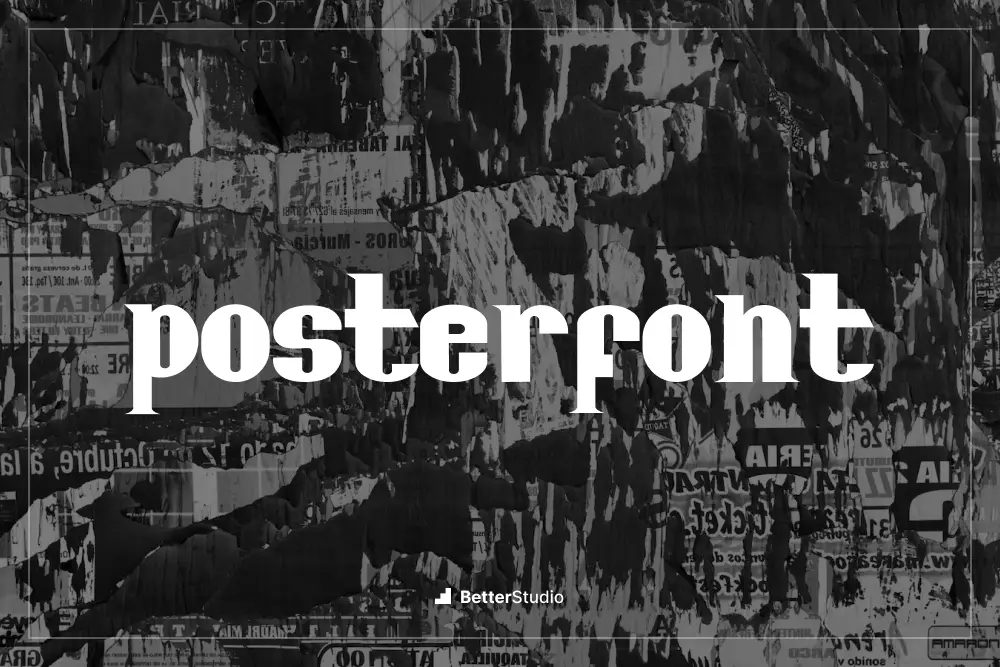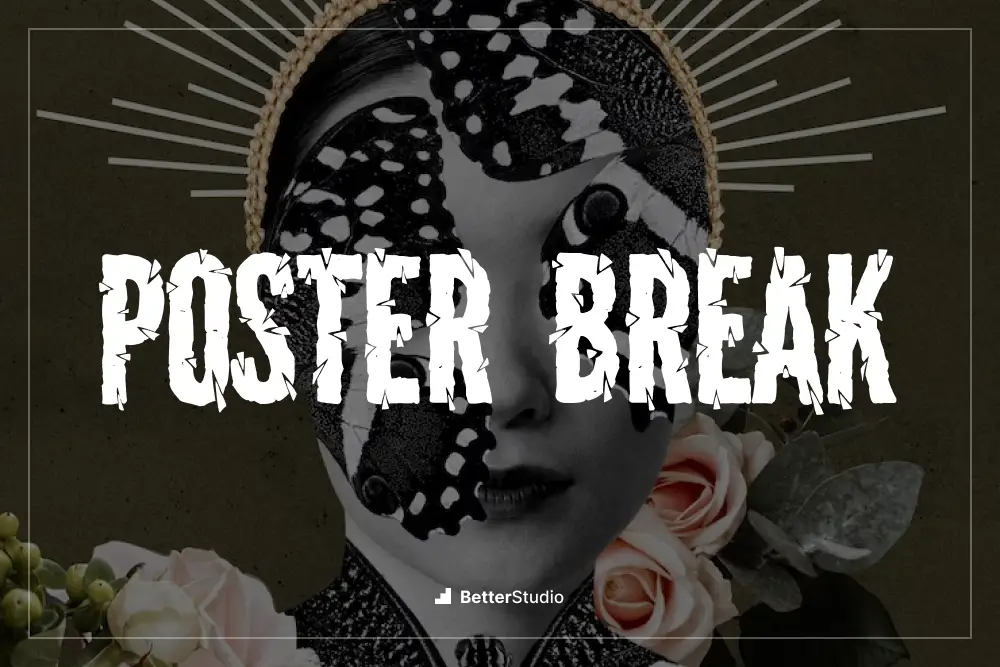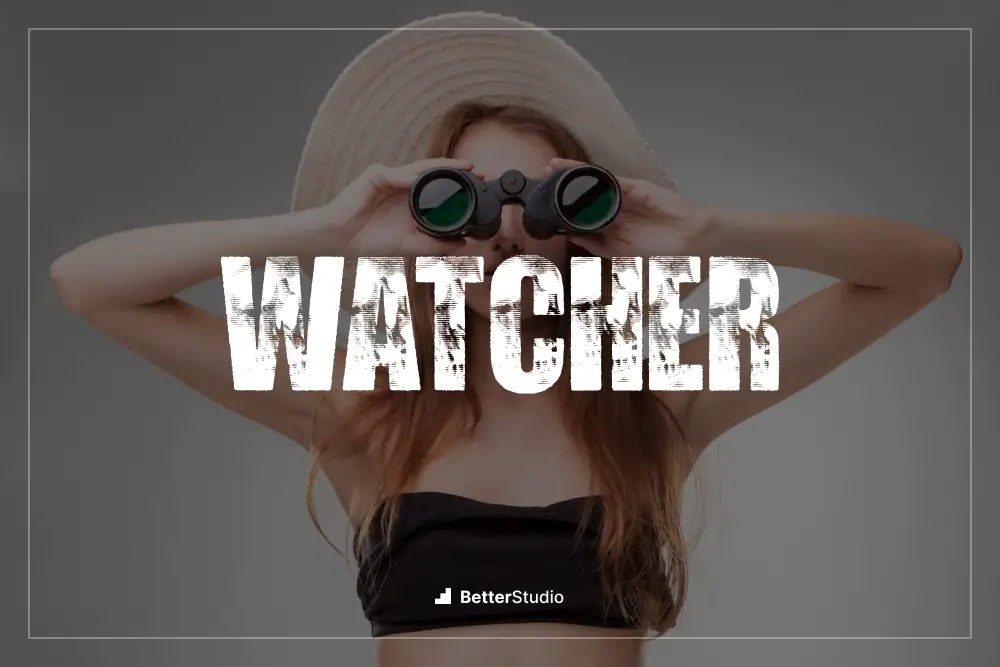
2023 年 36 種最佳海報字體(免費和付費)
已發表: 2023-07-25您是一名平面設計師,正在尋找完美的字體來改進您的海報設計項目嗎? 我們列出的 36 種最佳海報字體就是您的最佳選擇。 但您可能想知道,“我如何確定這些字體確實是最好的?”
我們的專家團隊在互聯網上搜尋最具視覺吸引力、易於閱讀且多功能的海報設計字體。 事實上,您是否知道使用正確的字體可以將消息的有效性提高高達 50%?
沒錯,只需將平淡、過度使用的字體替換為這些創新選項之一,就可以極大地提高設計的影響力。
在本文中,我們將引導您瀏覽我們的首選,並解釋為什麼每一個都脫穎而出。 從時尚的無襯線字體到大膽的襯線字體,甚至定制的手寫字體,每個項目都有適合的東西。
讓我們開始吧!
最佳高級海報字體
最佳優質海報字體可以以其獨特和專業的設計將您的項目提升到一個新的水平。 不要錯過為您的項目尋找完美字體的機會,看看我們在本文中發現了什麼。
海報現代斯堪的納維亞
Poster Modern Scandinavian 是一種引人注目的現代顯示字體,具有三種樣式:常規、粗體和斜體樣式。 Adobe Poster 字體旨在幫助您實現您的設計,非常適合各種項目,包括婚禮書籍、剪貼簿標題、賀卡、徽標、短語等。
甲殼蟲
Beetels 是 Typefactory 為打印項目設計的一款強大而有趣的字體。 這種字體具有清晰、粗體的字符,一定會讓您的海報脫穎而出。 文件中包含大寫和小寫字母、符號和標點符號、數字、連字和替代符號。
Beetels 還支持多語言使用。 對於為 Canva 尋找海報字體的圖形設計師來說,這種字體是一個絕佳的選擇,因為它易於閱讀且具有很強的視覺衝擊力。
拉里薩
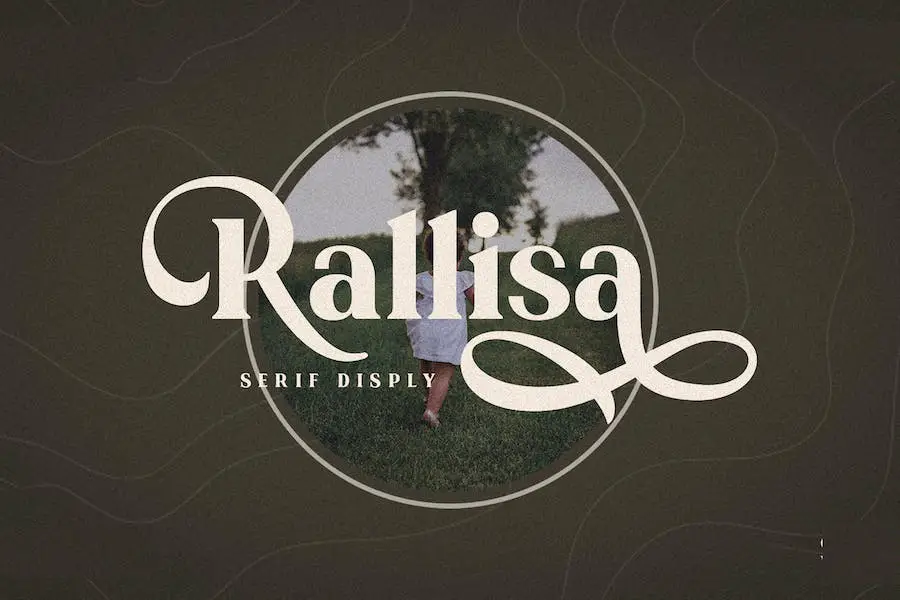
Rallisa 是一種時尚的襯線字體,可用於各種設計。 它非常適合食品菜單、海報、傳單和印刷品,為您的項目增添一絲精緻和優雅。 通過 Rallisa,您可以探索無限的可能性並創造出令人驚嘆的設計,給您的客戶和觀眾留下深刻的印象。
對於正在尋找高質量海報字體以增強其項目並使其脫穎而出的圖形設計師來說,該字體是理想的選擇。
Rallisa 優雅而現代的風格非常適合任何需要精緻、專業和獨特的設計。 海報字體可以合併到您的 Figma 設計中,使其成為數字項目工作人員的絕佳選擇。
奇思妙想
Whimsy 是一種完全手工製作的現代海報字體。 它有一種幻想和異想天開的感覺,這使得它適合一系列應用,包括標題、製作、品牌和報價。 這種字體非常適合任何需要一點奇思妙想的東西,包括 T 卹、海報、邀請函、包裝、書籍封面和卡片。
使用 Whimsy 最顯著的優勢之一是它具有獨特而迷人的外觀,可以使任何項目脫穎而出。
這種異想天開的字體增添了一絲創造力和趣味性,使其非常適合從兒童書籍插圖到復雜的品牌推廣等一系列項目。
動作英雄
Action Hero 是設計的終極海報字體,具有四種全大寫變體,具有完整的大寫和小寫字符、數字、標點符號和下劃線。
這種字體具有無窮無盡的創意選項,因此您無需重複字符,使其非常適合實現真實的手繪外觀標題設計。
航天發射場單線
Cosmodrome Monoline 是一種具有有趣而專業設計的字體。 這種字體非常適合海報、標牌、徽標等。
它還包括標準和擴展拉丁字符、連字以及一整套符號和數字,以提供多語言支持。 Cosmodrome 用途廣泛,使其成為未來主義和女性化項目的合適選擇。
波音
Wavetone是一種顯示型字體,從經典廣告和電影海報中汲取靈感。
它用途廣泛,適合多種用途,包括標題、徽章、徽章、邀請函和賀卡。 該字體結合了復古元素和 OpenType 功能,可幫助您在設計中創建和諧且有吸引力的信息。
達克斯坦
Darkstein 是一種怪異的萬聖節字體,它將把您的創意項目提升到一個新的水平。 它非常適合海報、電影標題、書籍封面和許多其他設計項目。 無論您是計劃萬聖節派對還是想要創造恐怖的設計,Darkstein 都能滿足您的需求。
這種字體的最大特點之一是它既有趣又可怕,使其非常適合任何萬聖節主題的設計。 其恐怖風格的設計營造出一種恐怖而有趣的氛圍,一定會讓每個人都感受到萬聖節的氣氛。
恐龍駝鹿
Dino Moose 是一種有趣而活潑的字體,可以提升任何項目的水平。 它具有大小寫選項,非常適合書籍封面、產品包裝、邀請函等。
國際字形功能和多語言支持使其成為多種語言的理想選擇。 更不用說,它包括三個帶有數字和符號的字體文件,以增加多功能性。
哈根
Hagen 是一款時尚現代的字體,從時尚前衛中汲取靈感。 它有兩種重量:常規型和時尚型,採用金屬製成,經久耐用。
該字體非常適合為電子節日創建徽標和設計引人注目的海報。 憑藉其前衛而獨特的風格,哈根對於那些希望通過精緻的方式增強其項目的設計師來說是一個不錯的選擇。
克萊德爾
Kleader 致力於用完美的字體增強您的設計。 字體就是一個很好的例子。 其純正的老派風格的靈感來自於經典的海報字體。 該系列包括襯線字體和無襯線字體,每種字體都有三種不同的字體可供選擇——常規字體、粗體字體和印章字體。
此外,您還可以訪問一些額外的插圖,使其成為一種多功能且富有創意的字體選擇。 It Font 甚至還包括用於添加設計選項的連字。
路徑腳本
Pathout Script 是一種腳本字體,以其粗體和流暢的風格而聞名,非常適合需要優雅而戲劇性的設計。
它具有大寫和小寫字符、數字、標點符號以及每個字符的一系列變體,其中包括 OpenType 替代項、常見連字和其他花體,使您的設計可以完全自定義。
滴
對於想要為項目添加獨特風格的圖形設計師來說,Drip 是一款必備字體。 該字體採用時尚的液體/快速風格,非常適合較大尺寸,並且在海報、書籍/專輯封面和徽標上效果非常好。
該字體幾乎包含每個字母的替代版本,可以通過切換大寫鎖定來訪問這些版本。
使用 Google Poster Fonts 優化的 Drip 增強您的設計並將其提升到新的水平。 這種字體的時尚設計和獨特風格使其成為尋求創建傑出項目的設計師的絕佳選擇。 試一試; 你不會失望的!
維特里斯
Wetris 是一種多功能液體顯示字體,每個字母有 10 種樣式,可組合成可定制的網格系統。 這種迷幻圖形現代手工風格非常適合希望為其項目添加獨特風格的設計師,無論是海報、報紙雜誌、Instagram、在線還是品牌推廣。
因此,如果您正在尋找 Word 海報字體,那麼 Wetris 是您的最佳選擇。 其獨特的風格、多功能性和易用性使其成為您設計工具庫的絕佳補充。 今天就嘗試一下,邁出創建令人驚嘆、專業的、引人注目的項目的第一步。
看過
Watched 是一種新字體,具有獨特、古怪和輕鬆的風格。 大寫字母具有明顯的變化,而小寫字母的組合則創造出引人注目的書寫風格。
這種字體非常適合電影標題,尤其是知名電影,並且將使您的項目脫穎而出。 嘗試觀看並親自看看有何不同!
該字體包括標準字形和多語言重音,使其成為各種項目的多功能選擇。 通過 Watched,您可以成為關注的焦點並保持優雅的外觀。
總的來說,如果您正在尋找一種兼具獨特性、風格和檔次的字體,那麼 Watched 是一個完美的選擇 - 特別是對於電路板上的海報字體。
紅色億萬富翁
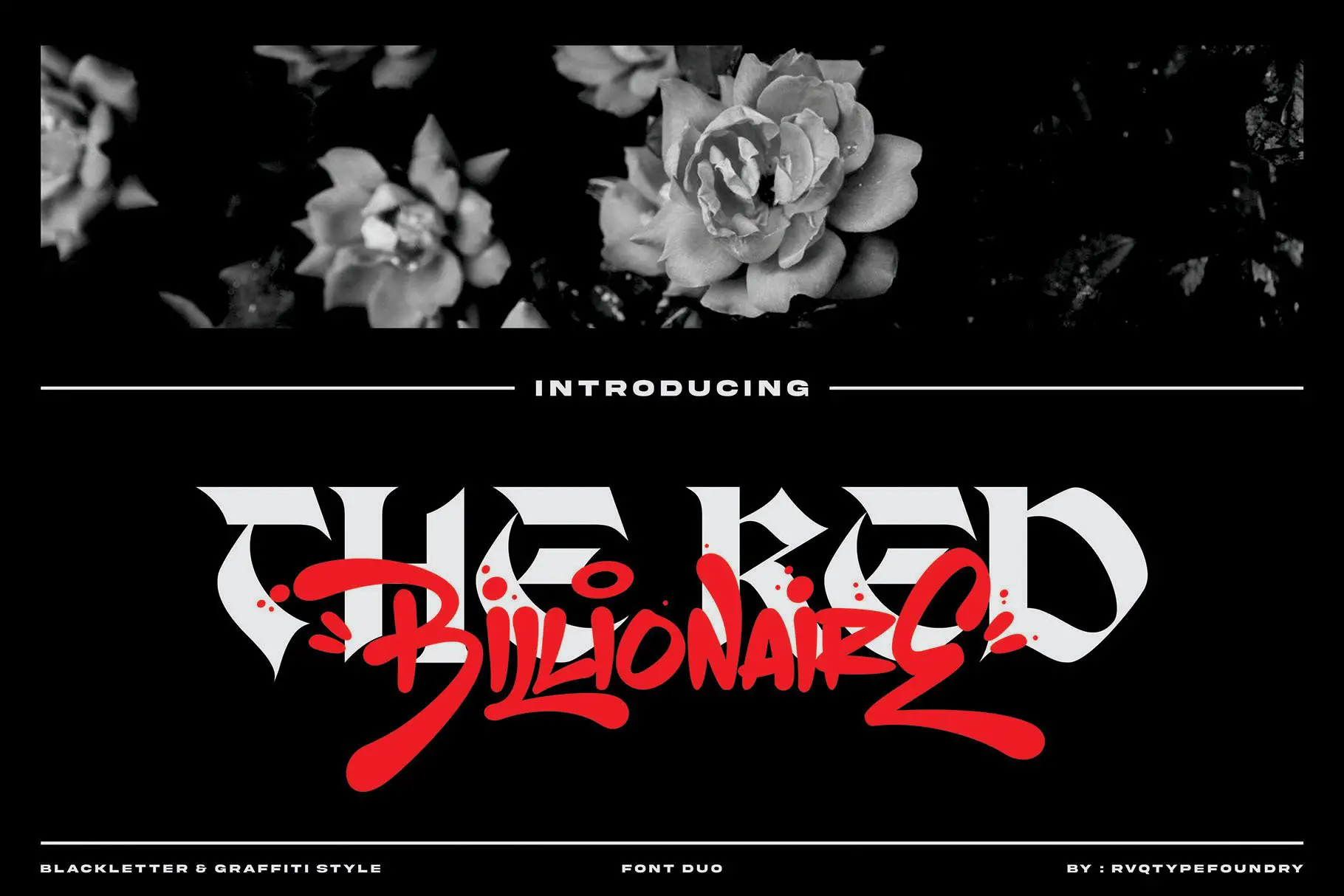
Red Billionaire 是 Rvq 字體鑄造廠的一款新字體,是一款兩用字體,非常適合各種項目。 該字體具有全套大寫和小寫字母,加上多語言支持、標點符號和額外字形,非常適合用於品牌、徽標、賀卡、文具設計、邀請函、T 卹、服裝、包裝設計和海報。
該系列中的字體非常適合製作引人注目的引人注目的海報。 海報字體也非常適合紋身設計。
Red Billionaire 字體對於此目的特別有用,因為它具有多種風格和真正脫穎而出的獨特字符設計。 無論您是要創建明信片、傳單還是廣告牌,這種字體都將幫助您給人留下大膽的印象。
脫衣舞
Strippy 是一種受 90 年代海報和圖形設計趨勢啟發而設計的字體,非常適合創建大膽而響亮的視覺效果。 其簡潔、方形和大膽的形式使其成為那些想要發表不容忽視的聲明的人的完美選擇。 該字體是手寫的,非常適合海報設計,為您的項目帶來獨特的個性化風格。
Strippy 最好的事情之一是它的用途非常廣泛。 無論您是為即將舉行的活動設計海報,還是只是想為您的品牌增添一些特色,Strippy 都能滿足您的需求。
血塊
Gore 是一個顯示字體系列,擁有大而粗的外觀,沒有曲線。 該字體非常適合電影海報上的標題,與其他無襯線字體和腳本字體完美搭配。 該字體有常規版本和粗糙版本,包括多語言大寫字母、數字和標點符號。
該字體的優勢在於它能夠傳達強有力的信息,使其成為任何電影海報的完美選擇。
粗糙的版本為文字增添了獨特的質感,為任何設計增添了一絲真實感。 毫不奇怪,戈爾成為那些想要製作引人注目的電影海報的設計師的熱門選擇。
爵士馬里諾
Jazz Malino 字體是任何設計師收藏的完美補充。 這種新字體帶有所有大寫類型、數字、標點符號、連字和多語言支持,包括德語、葡萄牙語、丹麥語等。
它不是普通的顯示字體,因為它是專門為獨特的標題、顯示文本和有彈性、隨機的外觀而創建的。 非常適合品牌、邀請函、展示、標題、活動名稱、博客文章、海報、社交媒體故事、標題等。
邁阿密
Miamo 是一個字體集,包括六種不同粗細的腳本字體和無襯線字體。 無襯線字體用途廣泛且現代,非常適合各種項目,例如徽標、廣告、包裝、書籍封面、現代雜誌和標題。 它的設計考慮到了對比度和可讀性,因此您的文本將很容易辨認。
手寫腳本字體優雅迷人,具有替代品和各種連字,使您的項目獨一無二。 它易於使用,並附帶 OpenType 功能,可以增強您的設計。
沃加特隆
Vogatron 是一款堅固且充滿未來感的無襯線顯示字體,它將帶您進入未來的境界。 該字體非常適合想要為項目添加科技感的圖形設計師。
它有 15 種重量,從壓縮到擴展,提供多種樣式可供選擇。 這意味著您在選擇 Vogatron 後無需再尋找其他選項。
北極星
Polaris 是一種具有未來派外觀和感覺的字體。 它擁有一組替代字母,使用戶有機會創建獨特的設計。 該字體包括大寫多語言字母、數字和標點符號,使其適用於各種設計項目。
對於任何想要為自己的設計組合增添現代感的人來說,它都是完美的選擇。 憑藉其前衛時尚的設計,它是海報、橫幅和數字設計的絕佳選擇。
另外,憑藉其替代字母選項,可能性是無限的。 用戶可以嘗試使用這些字母來創建引人注目的令人驚嘆的設計。
德萬特·尼奧特里克
Devant Neoteric 是一種現代無襯線字體,專為電影海報、標題、大寫字母、副標題、徽標設計和大橫幅而設計。
這種字體擁有獨特的屬性,可以增強任何項目的設計。 其乾淨、時尚的外觀,加上其多功能的風格,使其成為適合廣泛應用的優秀字體。
海報字體必須清晰、富有表現力和影響力,這是一個很難實現的平衡。 通過正確選擇字體,您可以傳達特定的情感,喚起懷舊之情,甚至將觀眾帶到不同的時間或地點。
選擇海報字體時,您應該考慮設計的基調、情緒和背景等因素。 您還應該牢記可讀性,因為某些字體在遠處可能難以閱讀。
另一件需要考慮的事情是字體與您的設計元素和品牌標識的兼容性。 此外,您應該始終測試不同的字體選項,看看它們在海報上的外觀,並確保它們與您設計的其餘部分完美契合。
結論
在本文中,我們重點介紹了每個平面設計師都應該了解的 36 種最佳海報字體。 我們討論了選擇正確的字體來增強項目設計的重要性以及它如何吸引觀眾的注意力。 使用這些字體,您可以將海報設計提升到一個新的水平。